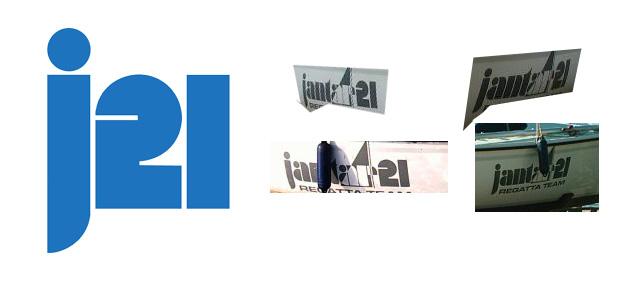
Suche eine BOOTS-Schriftart JANTAR 21.
vielleicht könnt ihr mir helfen. Ich suche die Schriftart auf dem Foto - mehr und bessere Quali habe ich leider nicht.
Eine polnische Werft hat von 1989 bis 2000 das Boot "Jantar 21" gebaut und in Deutschland vertrieben.
Eigentlich wurde das Boot standardmäßig nur mit dem Schriftzug "j21" ausgeliefert. Das "Jantar 21" voll ausgeschrieben stammt vermutlich von einem Eigner, könnte also heißen, dass es die Schriftart wirklich gibt.
Ich meine, keine Sonderanfertigung, oder so.
Ich habe schon diverse Seiten abgesucht, aber bin bis jetzt leider nicht fündig geworden.
Hallo, Futura black ist mir auch gleich ins Auge gesprungen. Leider nicht ganz, das kleine r zum Beispiel mit dem kleinen Viertelkreis ist ja ganz anders. Das kleine a ist aber fast genauso. Das ist schon mal was. Ich werde die Schrift versuchen nachzubauen, ich brauche nur ein Wort und so kann ich mich inspirieren lassen, wie wohl ein f oder ein e aussehen könnte.